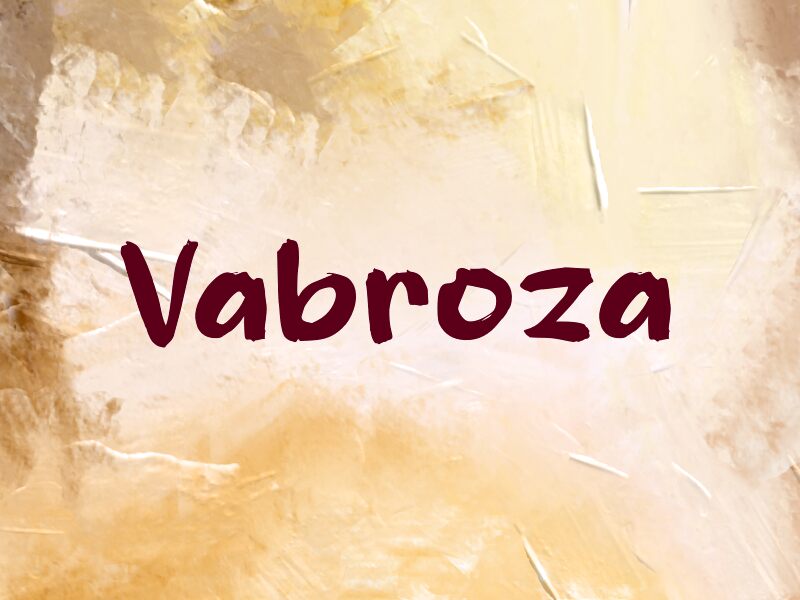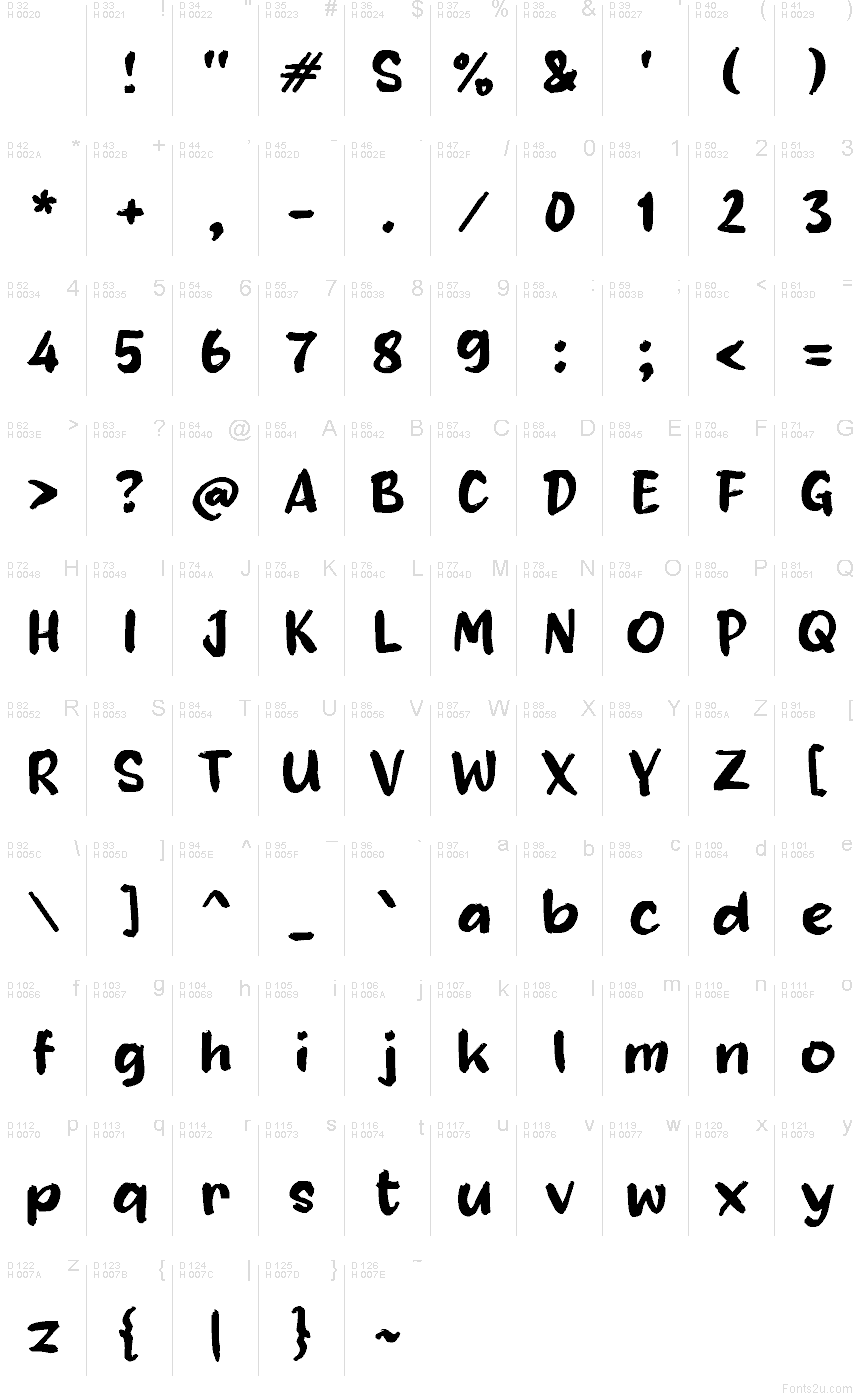
Vabroza
Vabroza від Wep — це безкоштовний шрифт із ефектом грубого мазка пензлем, швидким «малярським» ритмом та легким вуличним настроєм. Букви виглядають щільними, наче виведеними від руки, з тупими краями, нерівними з'єднаннями та округлими формами, що зберігають живу текстуру без зайвої «відполірованості».
Він ідеально впишеться в заголовки плакатів, музичну графіку, дизайн упаковки, обкладинки зінів або брендинг кафе, де безкоштовний шрифт має додати сирий, рукописний акцент, не перевантажуючи дизайн. Використовуйте його для коротких заголовків або обкладинок, коли хочете, щоб широкі мазки пензля та злегка недбалі контури самі задавали настрій.